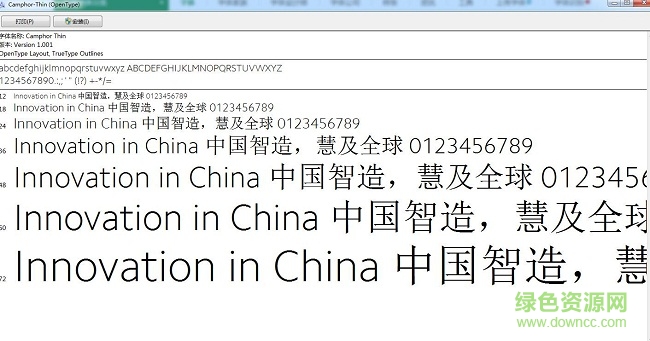
camphor thin字體
camphor thin字體是一款纖細(xì)的字體,該字體線條流暢干凈優(yōu)美,可以用在廣告設(shè)計(jì)、海報(bào)設(shè)計(jì)以及各類期刊雜志等各類排版設(shè)計(jì)中,需要的小伙伴快來(lái)綠色資源網(wǎng)下載吧!
camphor thin字體